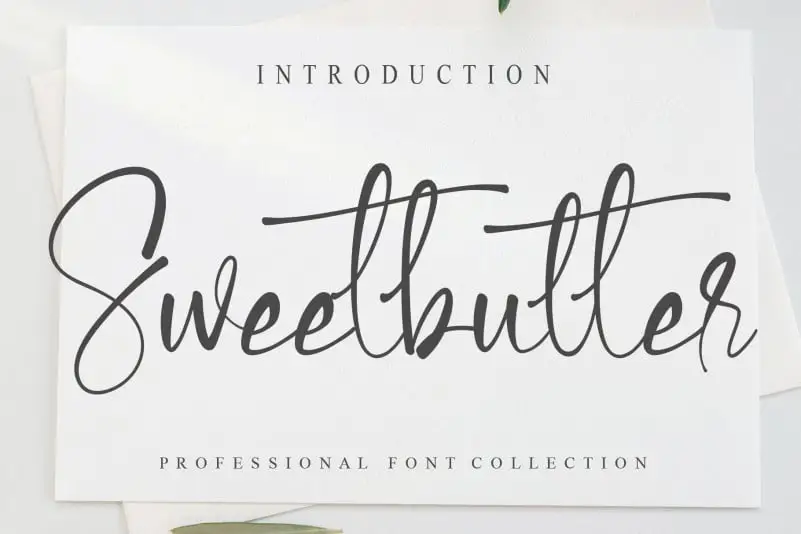
Sweetbutter Script Font – Download Grátis
A Sweetbutter Script Font é uma elegante escolha para quem busca um estilo à mão livre que transmite emoção e originalidade. Com um design fluido e expressivo, ela oferece uma experiência única e envolvente para seus projetos de design gráfico. Criada pelo designer creativeletter, esta fonte handwritten traz a sensação natural da escrita autêntica, ideal tanto para rótulos de marca quanto para o layout de capas de livros ou artigos visuais criativos. Seu traçado delicado e fluido combina perfeitamente com qualquer tipo de projeto que valorize uma apresentação única e pessoal. Não importa qual seja seu próximo projeto, a Sweetbutter Script Font certamente se encaixará perfeitamente em sua paleta de fontes.